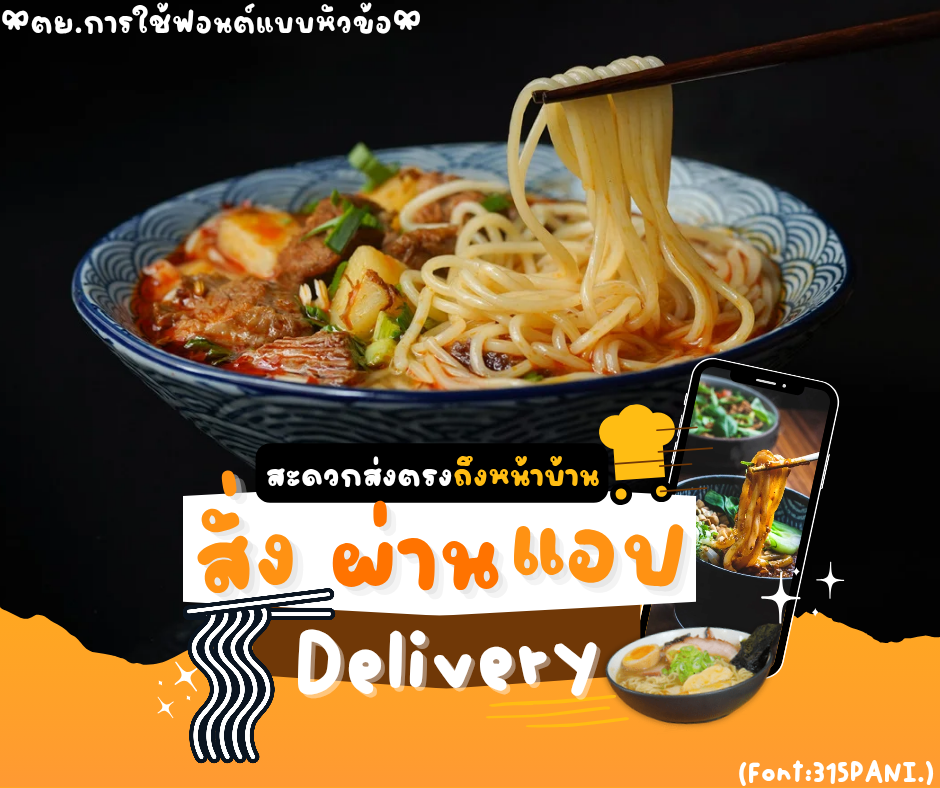
ฟอนต์ 315PANI.พรุ่งนี้
PANI.
ฟอนต์ตัวเข้ม ชุดนี้จุกๆ5ไฟล์
มาพร้อมกับฟอนต์โปร่ง เพิ่มให้อีกไฟล์ค่ะ
ชุดนี้น่ารัก ตัวเข้มๆเห็นชัด เจาะหัวเป็นวงรี
เหมาะกับการใช้งานหลากหลายแบบ
มือใหม่ก็ทำง่าย ไม่ยุ่งยาก ตัวอักษรเด่นชัดเจน
หรือใครเป็นสายแต่งคลิป ชุดนี้เหมาะเลยค่ะ
รูปรีวิวเป็นตย.การใ้ช้งานใน Canva นะคะ
วรรณยุกต์ไม่ลอยสูง อยู่ถูกตำแหน่ง
ทำให้ชิ้นงานดูพรีเมี่ยม
ตย.การออกแบบโดยใช้ฟอนต์บน Canva